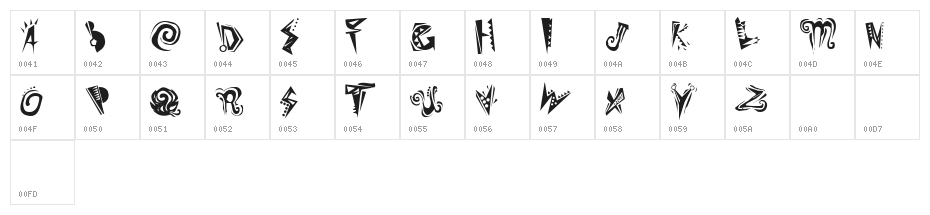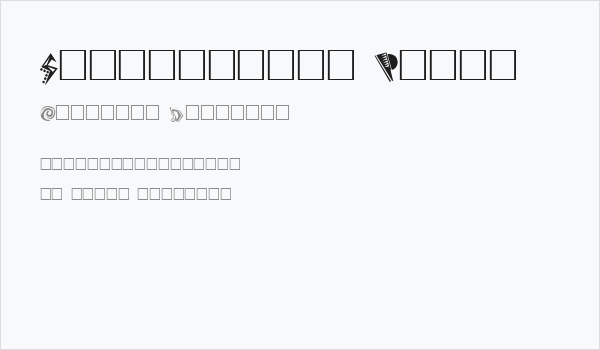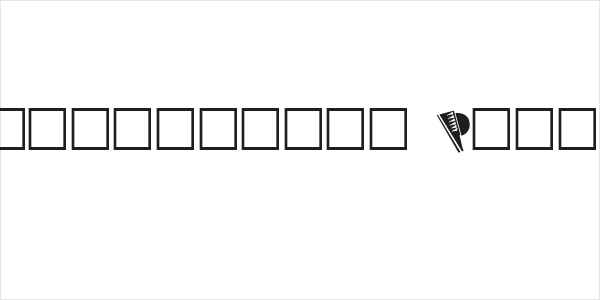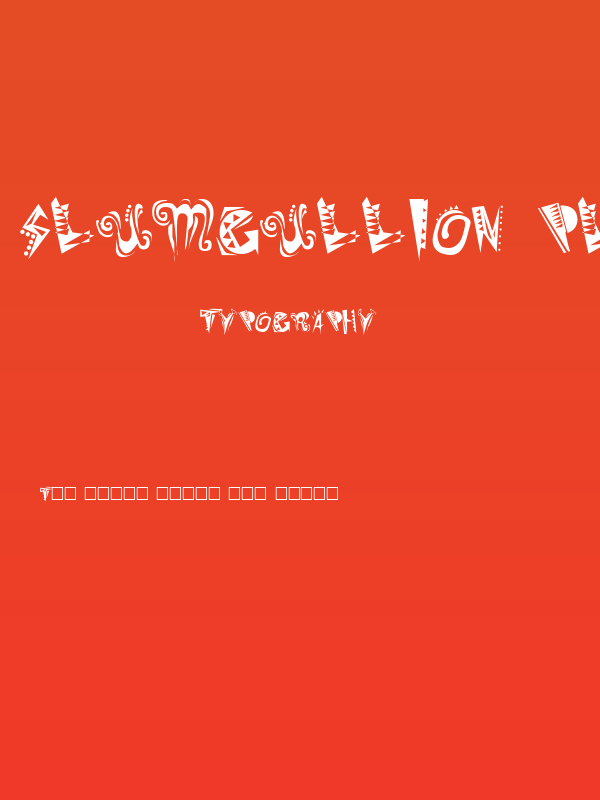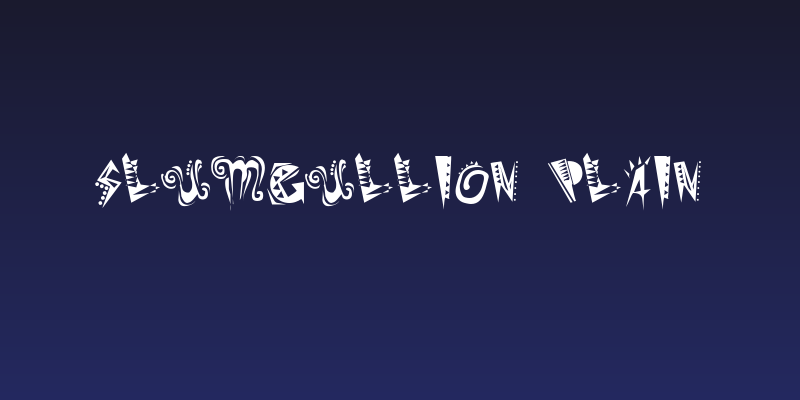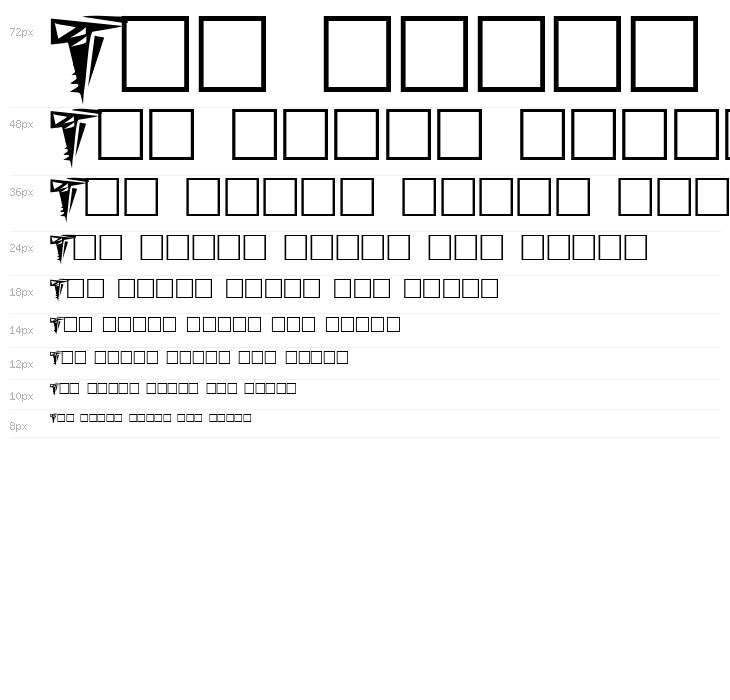
Slumgullion Plain Font
✎ Wild
| Progetti proposti | Ideal for posters, party invitations, event flyers, and any creative project needing a playful touch. |